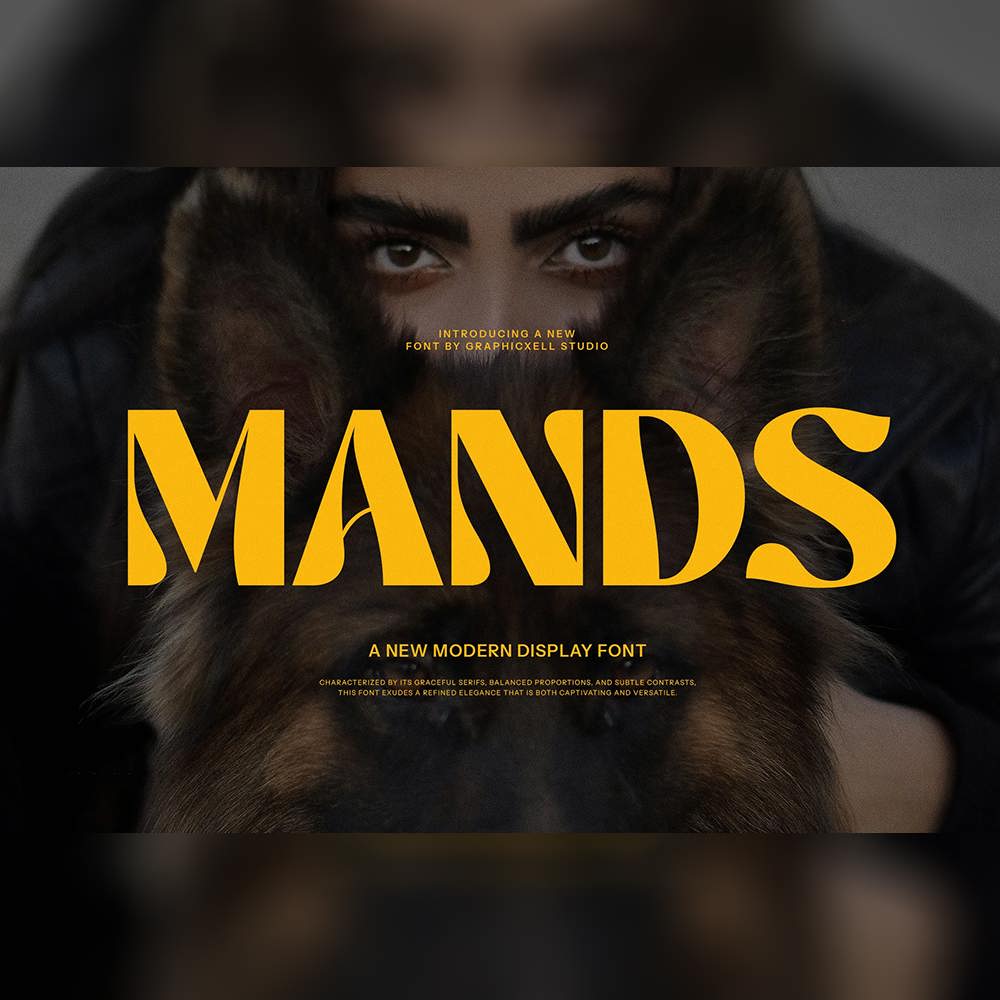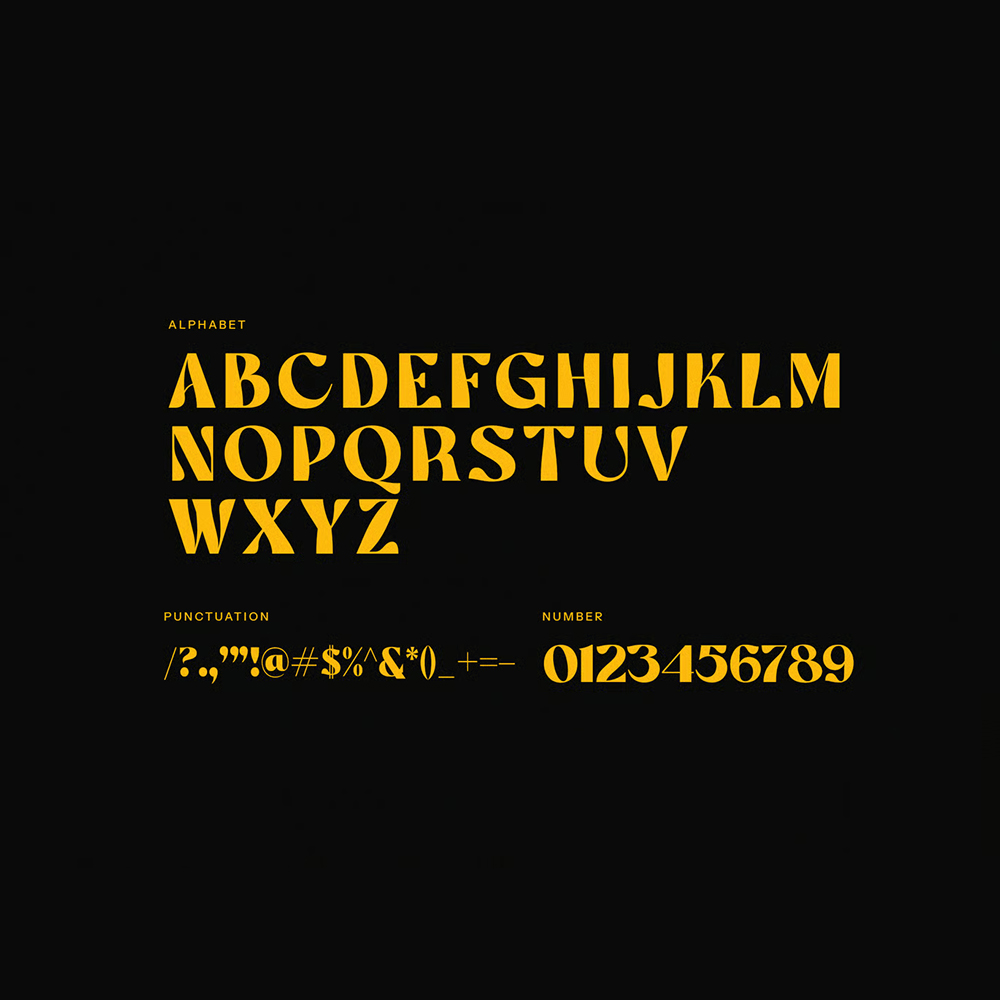
دانلود فونت انگلیسی Mands Font
فونت پرمیوم و انگلیسی Mands یک فونت شیک و مدرن سریف است که برای ایجاد ظاهری متمایز و حرفهای به پروژههای شما طراحی شده است. این فونت با شکلهای منحصر به فرد و خطوط متعادل خود متمایز میشود. در نتیجه، ضمن حفظ وضوح و خوانایی متن، به آن شخصیت میبخشد. بنابراین، برای برندسازی، طراحیهای سرمقالهای و پروژههای خلاقانه کاملاً مناسب است.
مزایای استفاده از فونت لاتین Mands Font چیست؟